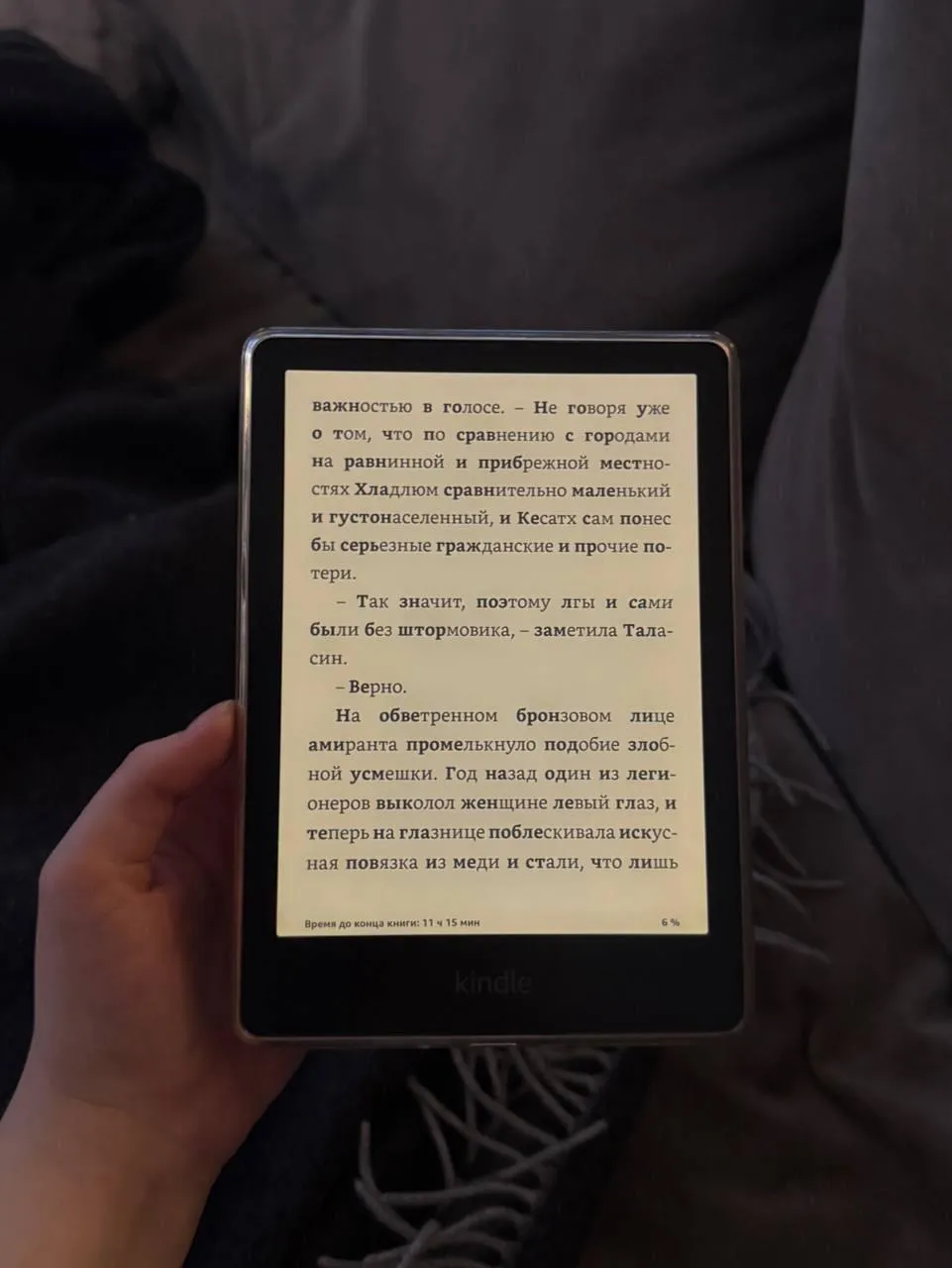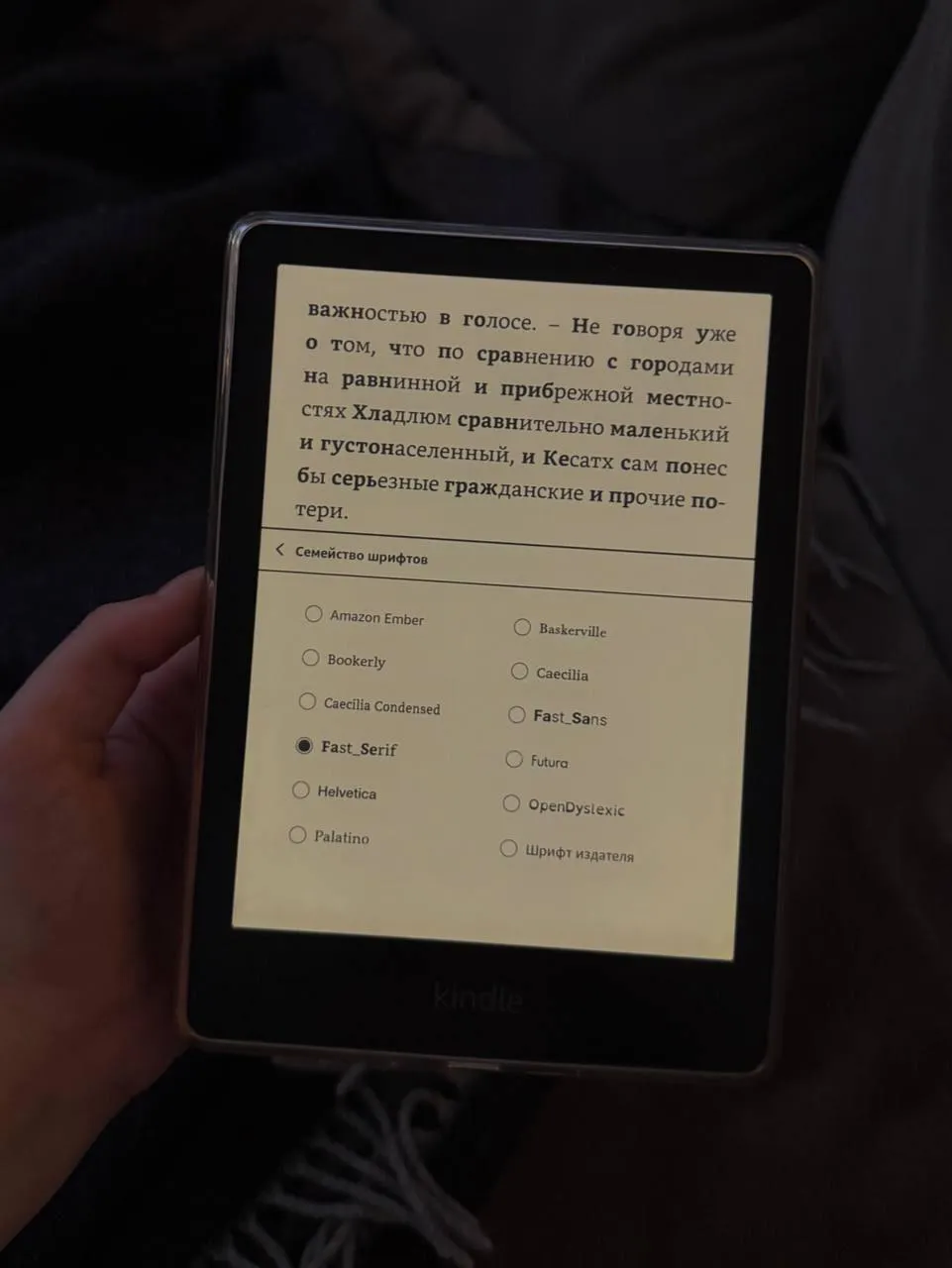
Шрифт для быстрого чтения
Этот шрифт также известен как специательный шрифт для тех, кто страдает от синдрома дефицита внимания и гиперактивности. Для обычного человека такие полужирные слова могут быть трудными для чтения, но для тех, у кого есть проблемы с концентрацией, такой шрифт – практически спасение.
На самом деле я видела очень много отзывов от разных комментаторов, и они категорически разнятся: кто‑то говорит, что он прекрасен, а кто‑то говорит, что при чтении очень часто спотыкается. А вам как?
Моё мнение -- мешает читать!
Там же полслова жирный шрифт, полслова - обычный.
Очень мешает.
Мне сначала мешало, а потом привыкла
Не удобно читать. Я пробовал так, мозг реагирует на выделенные части слов сразу на весь текст.
Да, для людей без сдвг и проблем с вниманием текст выглядит неудобным